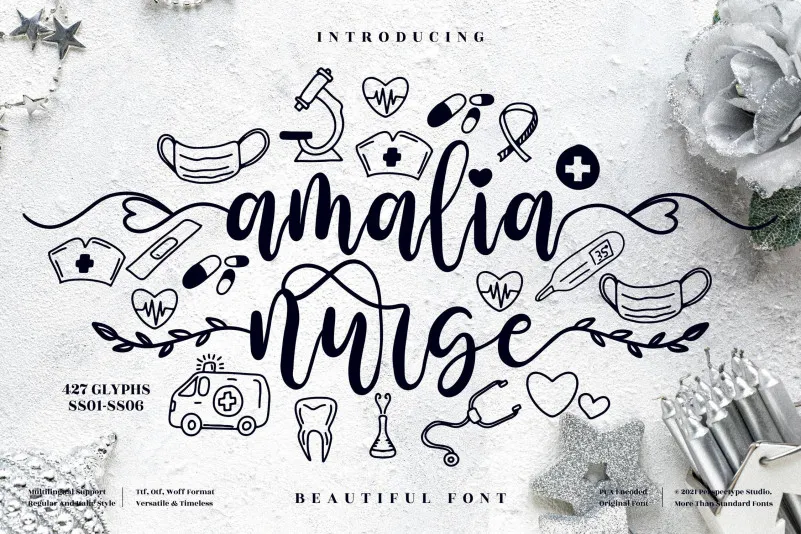
Amalia Nurse Font – Download Grátis
A Amalia Nurse Font é uma elegante letra círca que transpira sofisticação e classe. Ideal para quem busca uma aparência fresca e atraente em seus designs, esta fonte foi cuidadosamente projetada para aqueles que valorizam uma beleza única e distinta. Com PUA (Unicode) codificada, você pode acessar facilmente todos os caracteres e ganchos especiais desta fonte. Não é apenas um adorno casual, mas sim a eletricidade de um design gráfico refinado. Seja para um projeto editorial sofisticado ou uma campanha de marketing impecável, esta fonte é perfeita para aqueles que procuram um toque especial em seus trabalhos visuais.